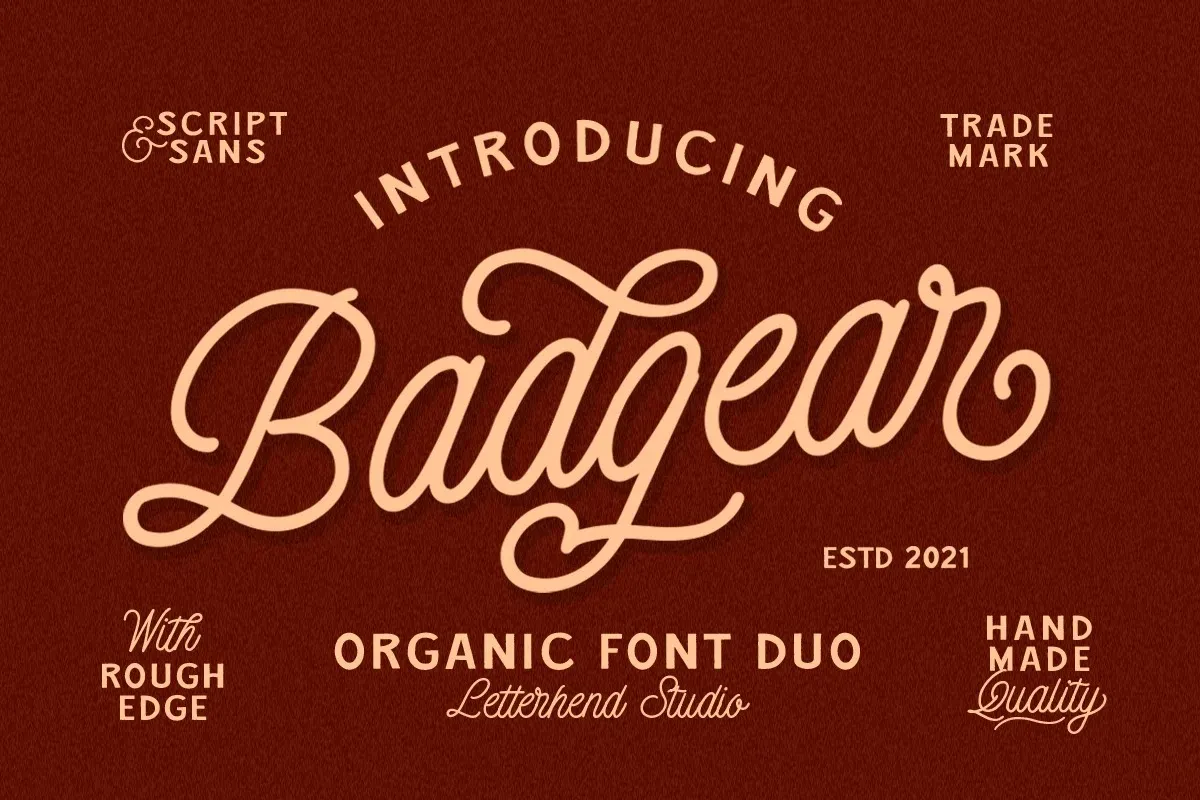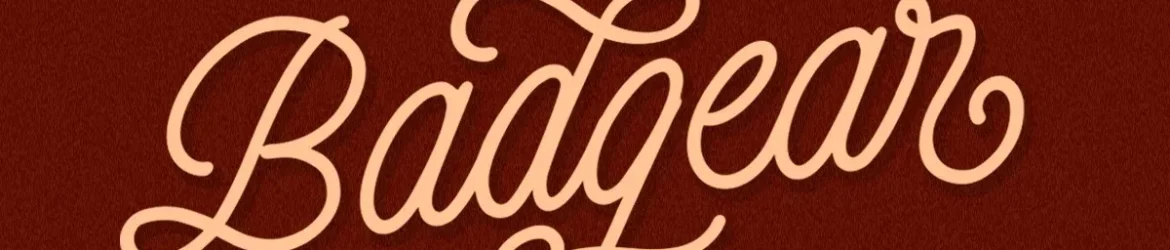
Badgear Font – Download Grátis
Esta é uma tipografia de selo monoline inspirada na cultura clássica do Oeste americano, com um toque retro que a torna natural e perfeita para aplicações variadas. A Badgear Font tem um estilo único que se destaca especialmente em logotipos, headlines e sinais, mas também funciona muito bem em cartões de convite, rótulos, logos, livros, revistas, cartões de felicitações ou embalagens. Suas linhas retas e formas geométricas criam um design elegante que se destaca sem deixar de estar em sintonia com a personalidade moderna da tipografia script, tornando-a uma opção perfeita para qualquer tipo de aplicação visual formal. Engane-se, você encontrará em Badgear Font uma fonte ideal para incorporar elementos retro e clássicos ao seu design contemporâneo.